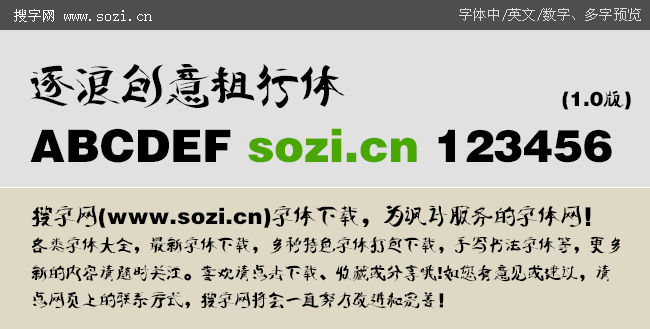
逐浪創(chuàng)意粗行體
搜字網(wǎng)提供一款逐浪創(chuàng)意粗行體中文書法字體下載,逐浪創(chuàng)意粗行體是一款手寫風(fēng)格的書法創(chuàng)意字體,該字體瀟灑大方、筆勢強勁奔放,整體效果十分出色。適合應(yīng)用于廣告設(shè)計、名片設(shè)計、包裝印刷、產(chǎn)品設(shè)計等應(yīng)用。本字體僅供個人學(xué)習(xí)使用,如需商用請聯(lián)系作者進行購買(作者主頁http://www.ziti163.com/index.shtml)。